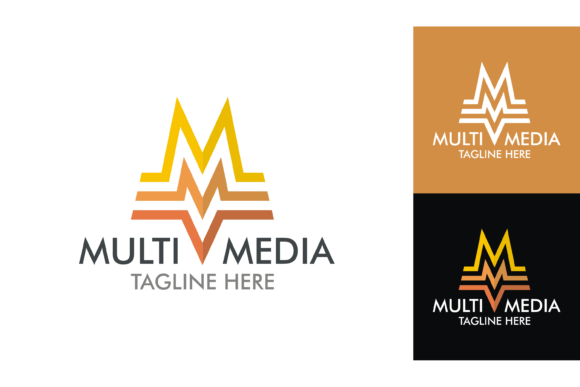
Multimedia Logo
การค้นหาองค์ประกอบการออกแบบที่เหมาะสมอาจเป็นเรื่องท้าทาย แต่ Multimedia Logo นำเสนอคอลเลกชันที่โดดเด่นซึ่งช่วยยกระดับงานของคุณได้ทันที
สร้างขึ้นอย่างแม่นยำ Multimedia Logo ให้เวกเตอร์ที่สะอาด พิมพ์ตัวอักษรที่ราบรื่น และใบอนุญาตเชิงพาณิชย์เพื่อความสบายใจ
ไม่ว่าคุณจะสร้างผลิตภัณฑ์ POD (Print on Demand) คำเชิญงานแต่งงาน หรือกราฟิกโซเชียลมีเดีย Multimedia Logo ก็เหมาะสมอย่างยิ่ง